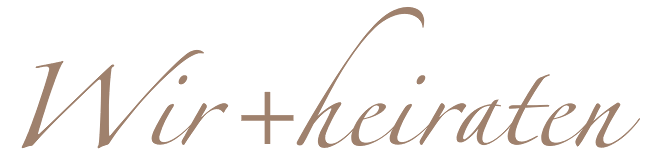
Suche die schöne Schriftname
ich bin neu hier und hoffe, dass Ihr mir helfen könnt.
Ich möchte die schöne Schrift für den persönlichen Gebrauch verwenden, jedoch kann ich nicht herausfinden,
um welche Schriftart es handelt.
Ich habe mal ein entsprechendes Bild angehängt.
Wäre echt super, wenn mir jemand helfen könnte.
Gelöst von Gast Schnitzel
Das ist die Zapfino …
Das ist genau die Name des Schriftart.
Das war so schwer nicht – das hat ja noch nicht mal Bertel aus der Versenkung gelockt ...
Ist ja mittlerweile fast die Edel-Comic-Sans  :-o